Top 5 Font viết tay Việt hóa free miễn phí
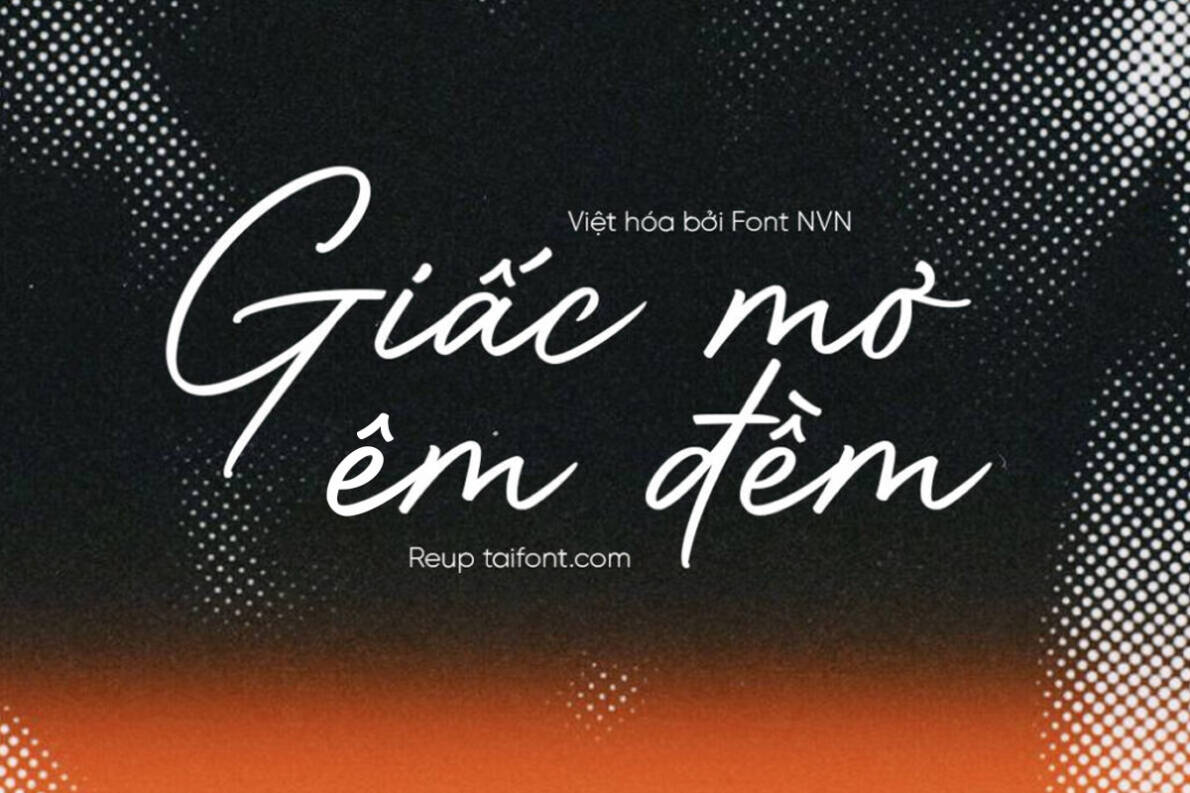
Top 5 Font viết tay Việt hóa free miễn phí, là những font chữ Việt hóa chữ ký đẹp dùng cho thiết kế quảng cáo, thiết kế thiệp cưới, thiệp mời.
Top 1: Font việt hoá MJ Charlotte Ornamental
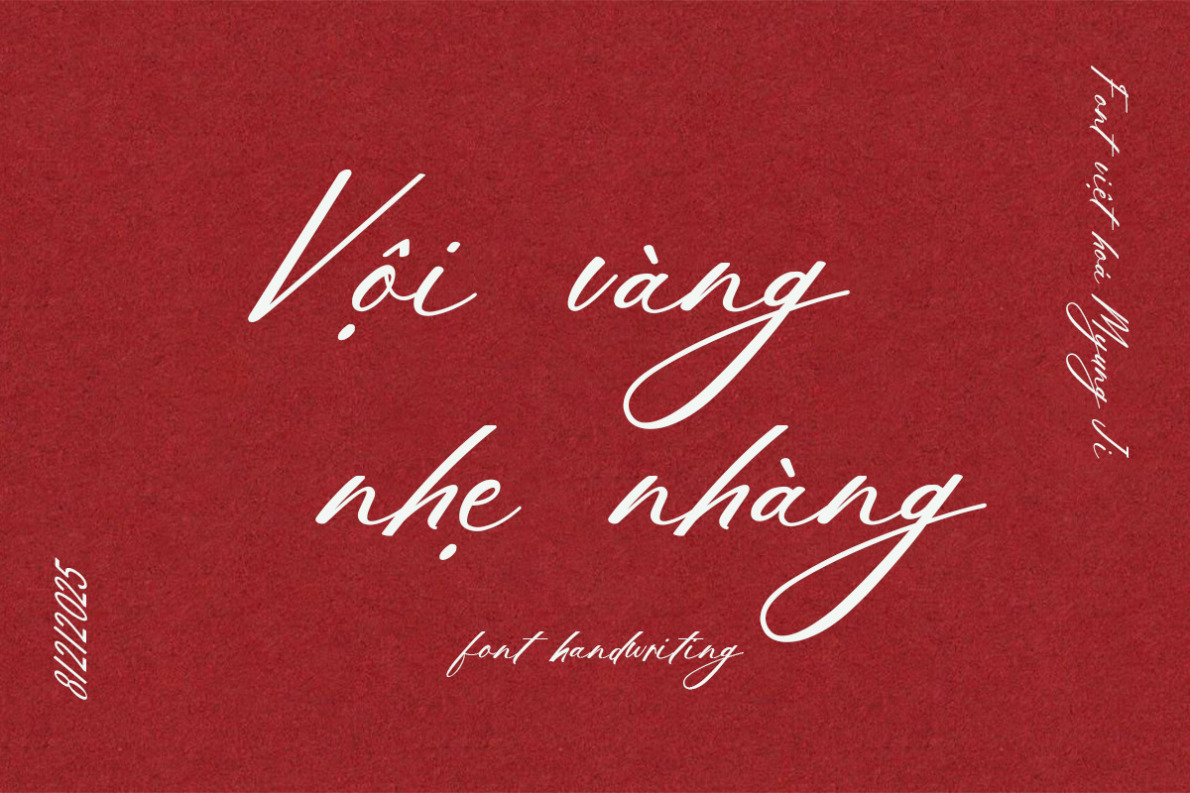
Top 2: Font việt hoá MJ Charming Valentines
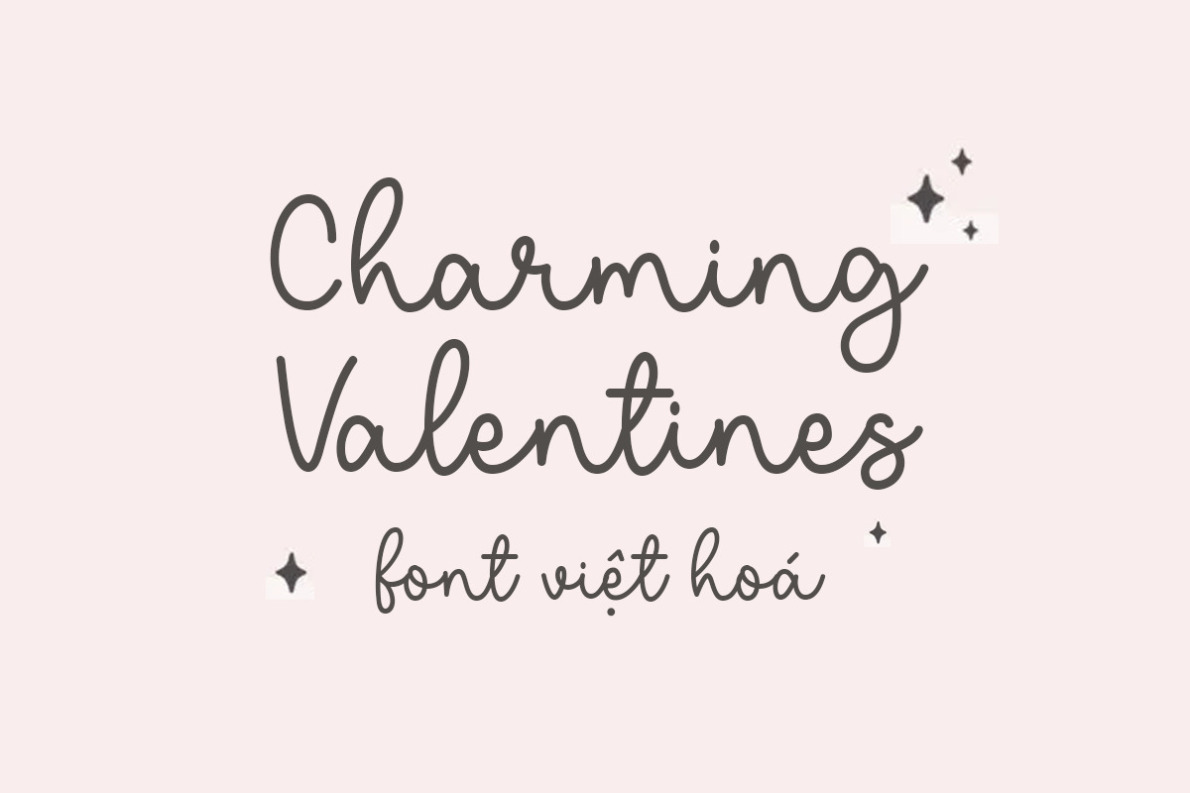
Top 3: Font việt hoá MJ LoveLy Love
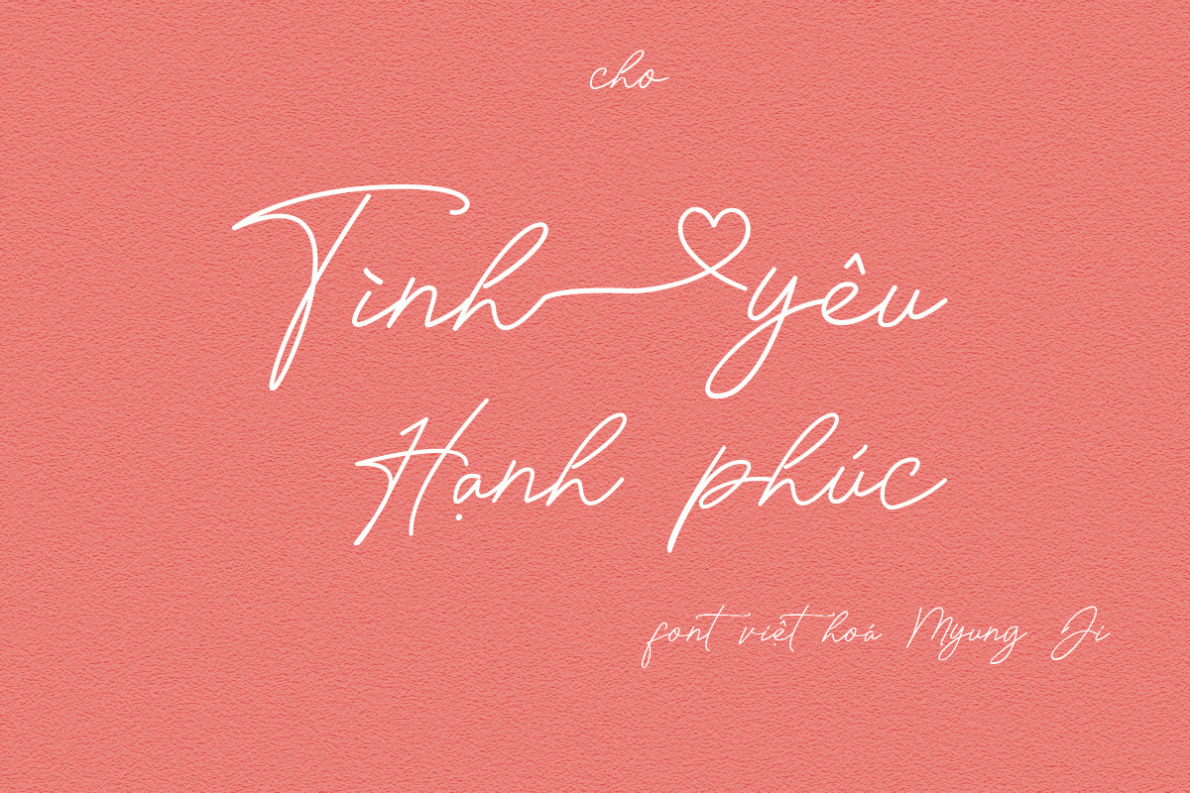
Top 4: Font việt hoá MJ Beautiful Athellin
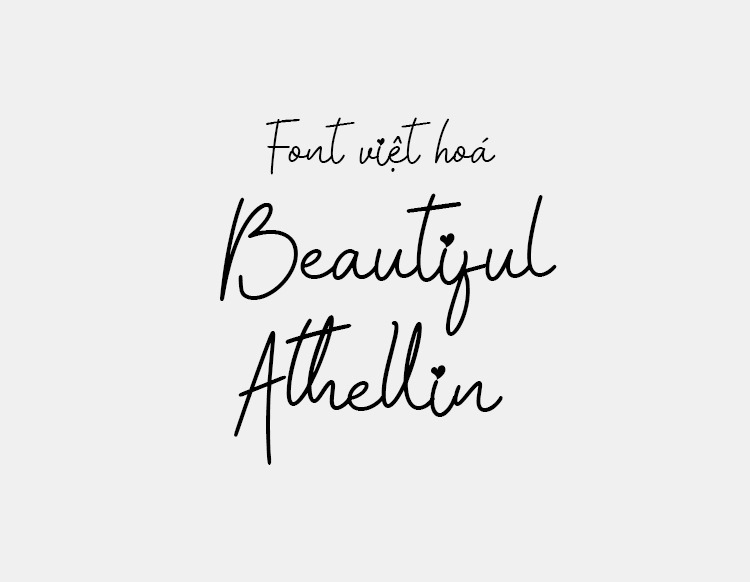
Top 5: Font Việt hóa NVN Motherland Signature